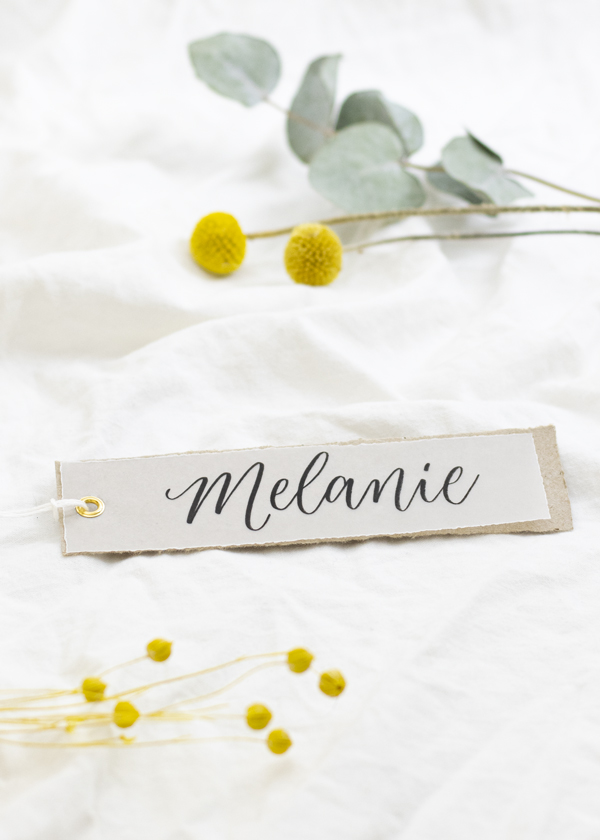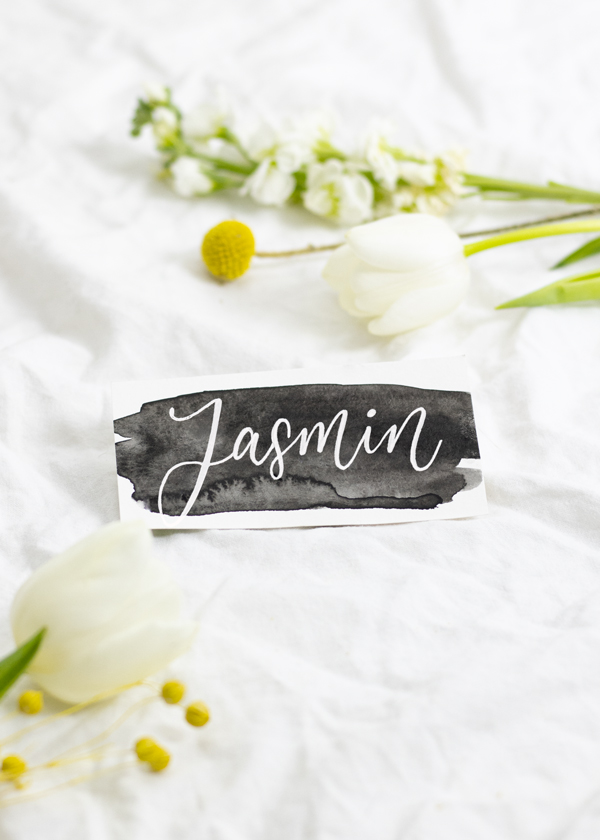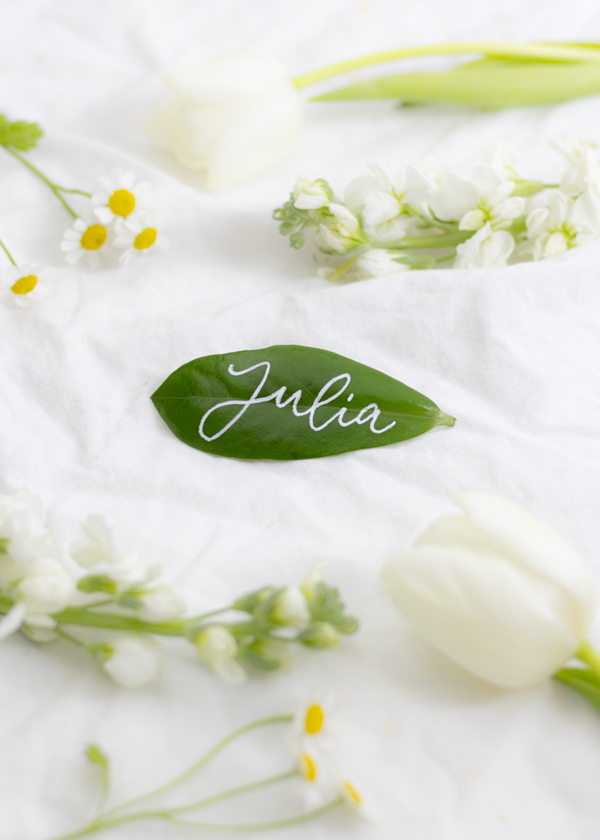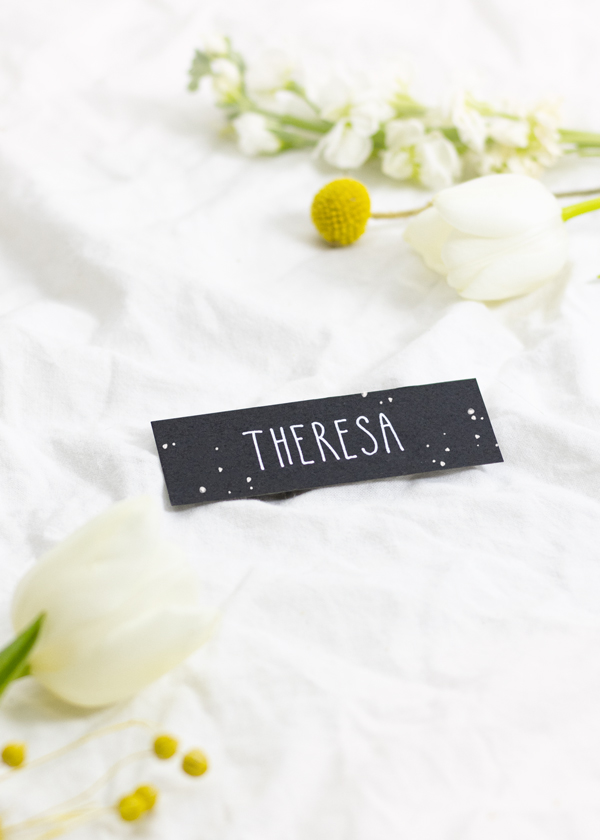
Wenn du deine Gäste mit liebevoll, handgemachten Namensschildern begrüßen möchtest, bist du hier richtig! In diesem Blogeintrag möchte ich dir 5 Ideen zeigen, wie du schöne Namensschilder selber machen kannst. Ich würde mich freuen, wenn ich dich vielleicht mit der ein oder anderen Idee begeistern kann! Und nun wünsche ich dir viel Freude beim Stöbern….
Idee no.1: Namensschild – schlicht und einfach
Wenn es eher schlicht und einfach, statt schnörkelig und schwungvoll sein soll, kannst du eine einfache Druckschrift wählen. Mit einem weißen Gelliner und einem dunklen Papier (z.B. schwarzem Tonpapier) kannst du auch mit der schlichten Druckschrift für einen besonderen Look sorgen.
Die Buchstaben:
Die Druckschrift besteht in diesem Beispiel nur aus großen Buchstaben. Für den besonderen Look, kannst du die Buchstaben schön schmal zeichnen und die Querstricke höher setzten, als bei einem gewöhnlichem Alphabet.
Idee no.2: Namen auf Blättern lettern
Für besonders naturverliebte Menschen habe ich eine ganz besondere Idee. Statt Papier eignen sich nämlich auch einige Pflanzenblätter besonders gut als Malgrund.
Die Buchstaben:
Um den zarten Charakter und die geschwungenen Formen des Blattes zu unterstützen, kannst du gut eine Schreibschrift verwenden. Versuche die Grundlinie dabei an einigen Stellen aufzubrechen, um ein leichtes Schriftbild zu erzeugen.
Idee no.3: Namensschilder selber machen mit Aquarell
Vielleicht hast du irgendwo noch alte Schmierblätter mit Aquarellübungen? Diese kannst du wunderbar nutzen, um schöne Namensschilder damit zu gestalten. Solltest du keine Übungsblätter mit Aquarellklecksen haben, kannst du die Hintergründe vorab anfertigen. Die Hintergrundfarben kannst du dabei ganz nach deinem Geschmack auswählen.
Die Buchstaben:
In diesem Beispiel habe ich die falsche Kalligrafie verwendet. Dabei wird zuerst der Schriftzug gelettert und im nächsten Schritt werden die Linien verdoppelt, die beim Schreiben von oben nach unten fließen.
Idee no.4: Platzkarte – Elegant mit Kraftpapier
Wenn du Namensschilder selber machen möchtest, die aus verschiedenen Papieren bestehen, kannst du Ösen benutzen, um die Papiere miteinander zu verknüpfen. Das Beste ist, durch die Öse kann das selbstgemachte Namensschild mit einem kleinen Band ergänzt werden, wodurch es zum Anhänger wird.
Die Buchstaben:
Um ein schönes, zartes Schriftbild zu kreieren, kannst du gut einen Brushpen mit feiner Spitze verwenden. Mein Favorit ist der Tombow Fundenosuke* mit harter Spitze. Wenn du mehr über das Brushlettering erfahren möchtest, schau mal hier: Brushlettering lernen.
Idee no.5: Moderne Platzkarte mit Watercolor
Auch mit Wasserfarben lassen sich schöne Buchstaben aufs Papier zaubern. Das Beste ist, Wasserfarben lassen sich untereinander mischen, sodass du deine herzallerliebste Lieblingsfarbe mischen kannst.
Die Buchstaben:
Wenn du die Buchstaben mit einem Pinsel letterst, entsteht schnell ein unkontrollierter Look dadurch, dass die einzelnen Haare schwer zu kontrollieren sind. Du kannst dir diese Eigenschaft zunutze machen, um bewusst ein unkontrolliertes Schriftbild im modernen Brushlettering-Stil zu erzeugen.